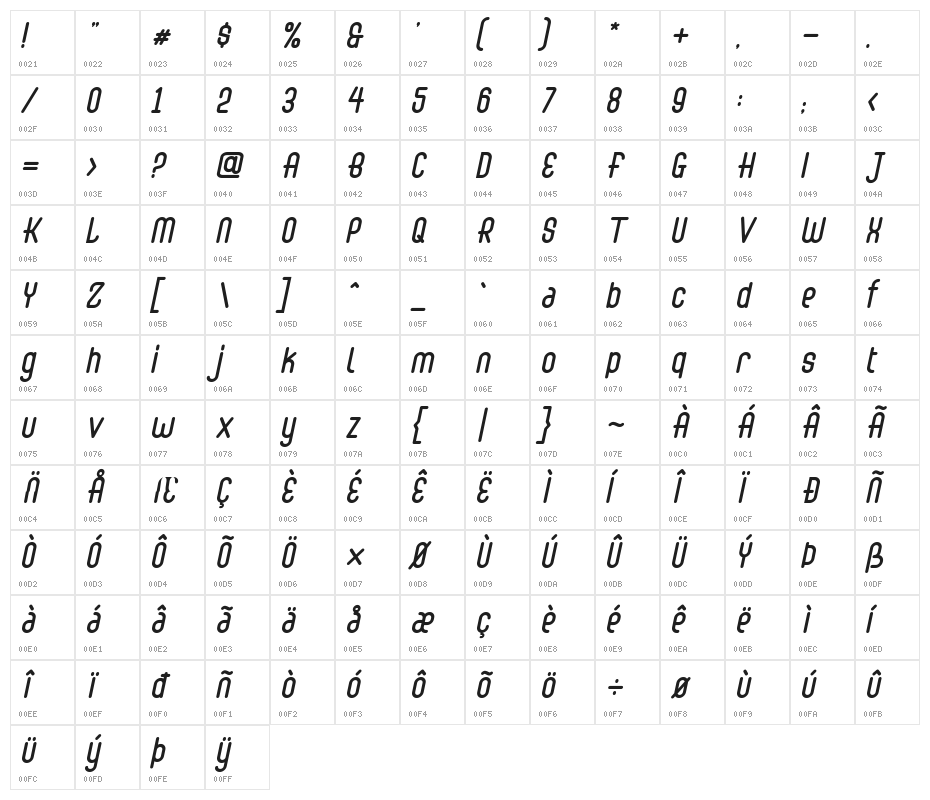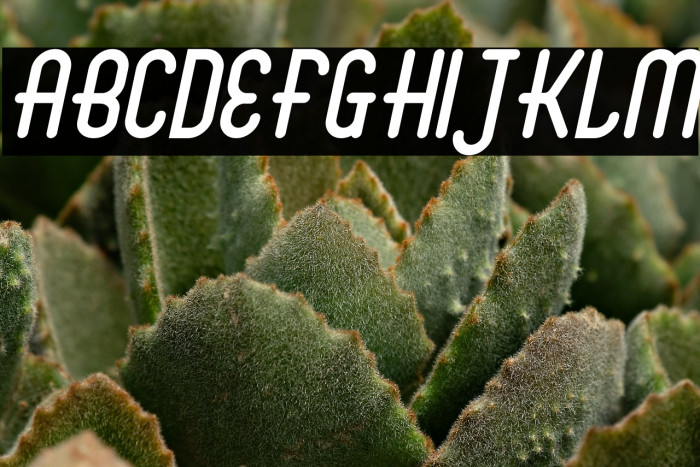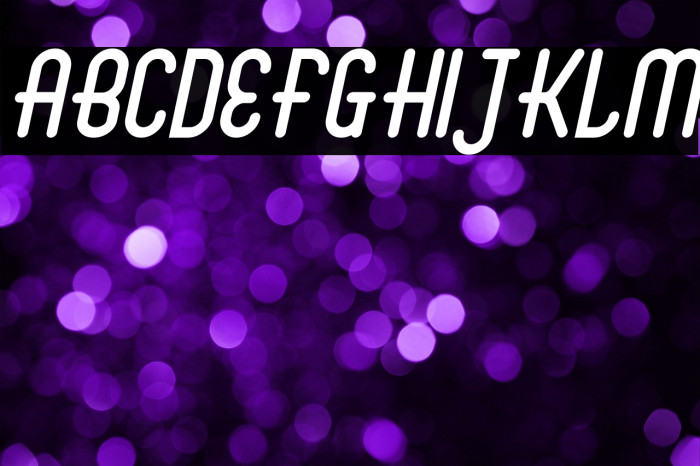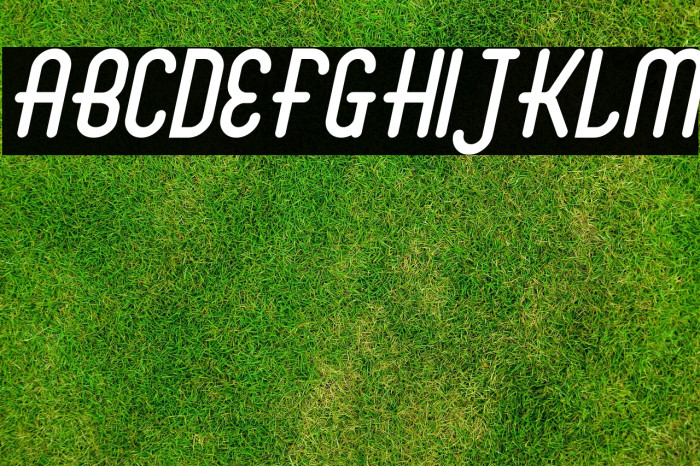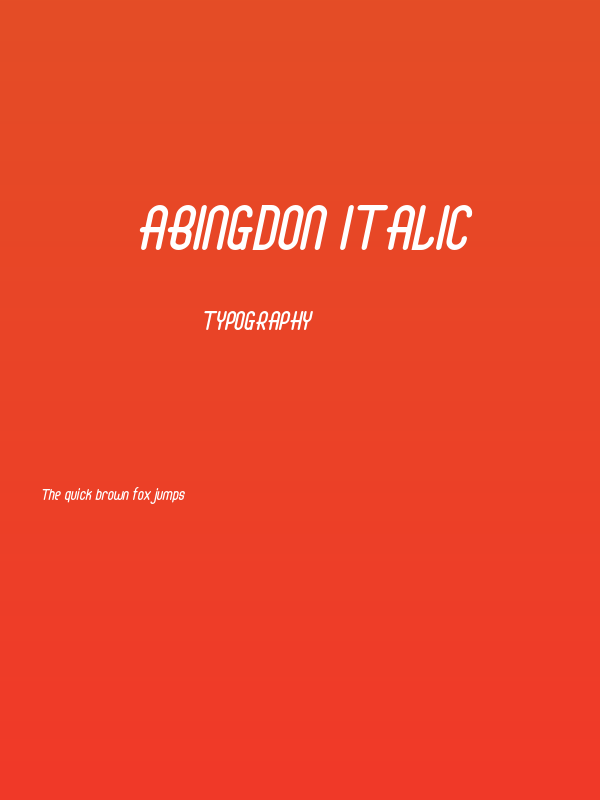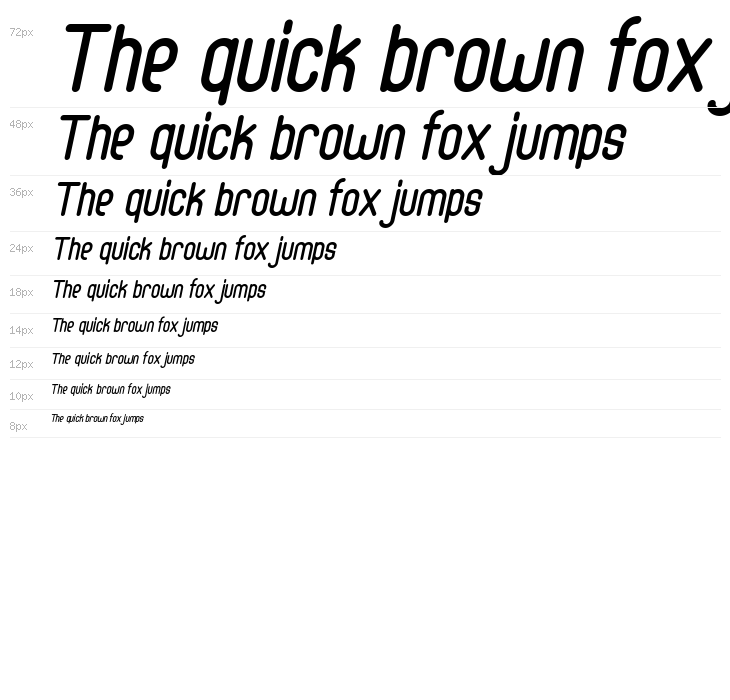
Abingdon Italic Font
✎ Round
| Caso d'uso | Headlines, Logos, Digital Media |
| Progetti proposti | Ideal for branding, advertising, and digital media projects where a modern and dynamic look is desired. |
Abingdon Italic